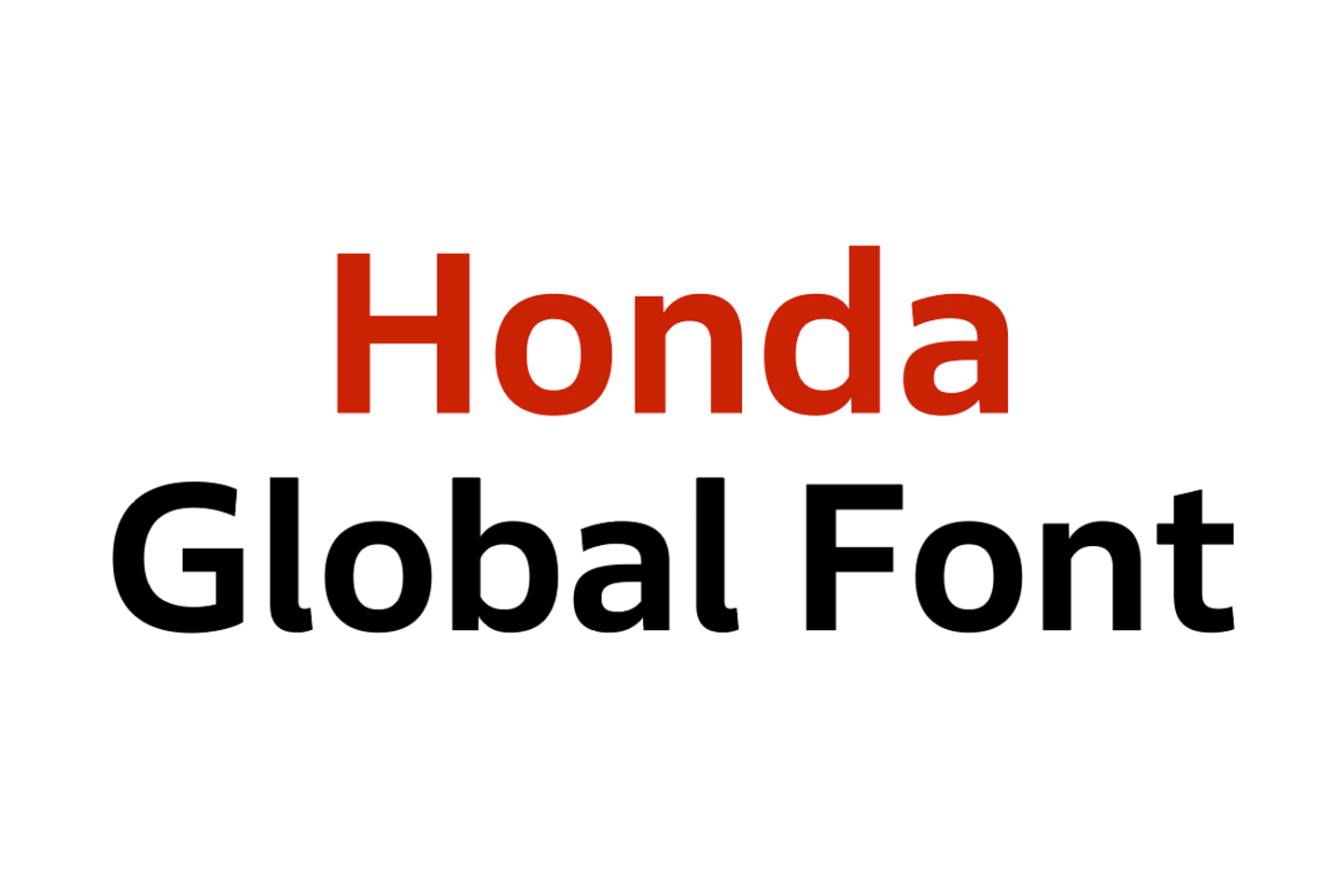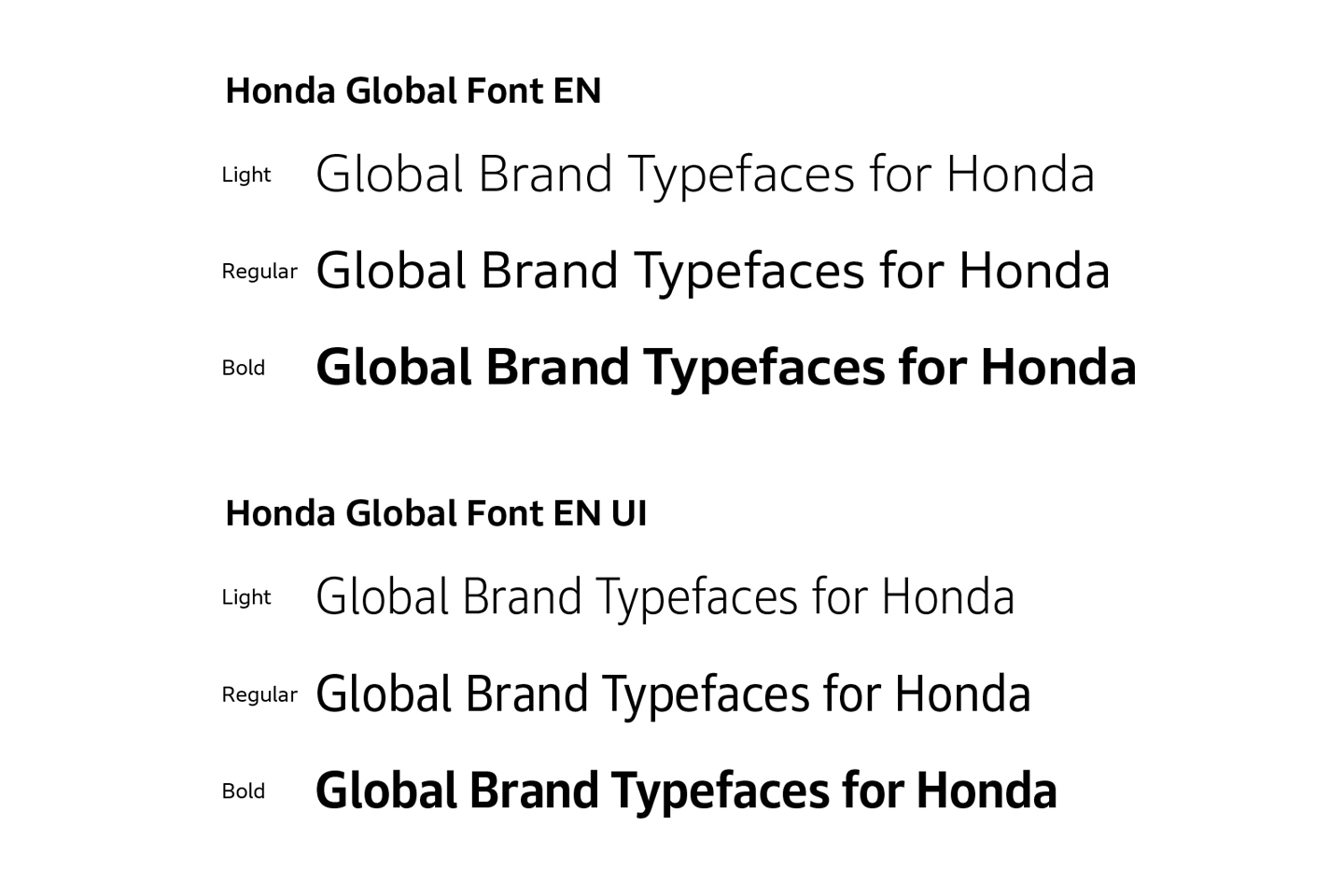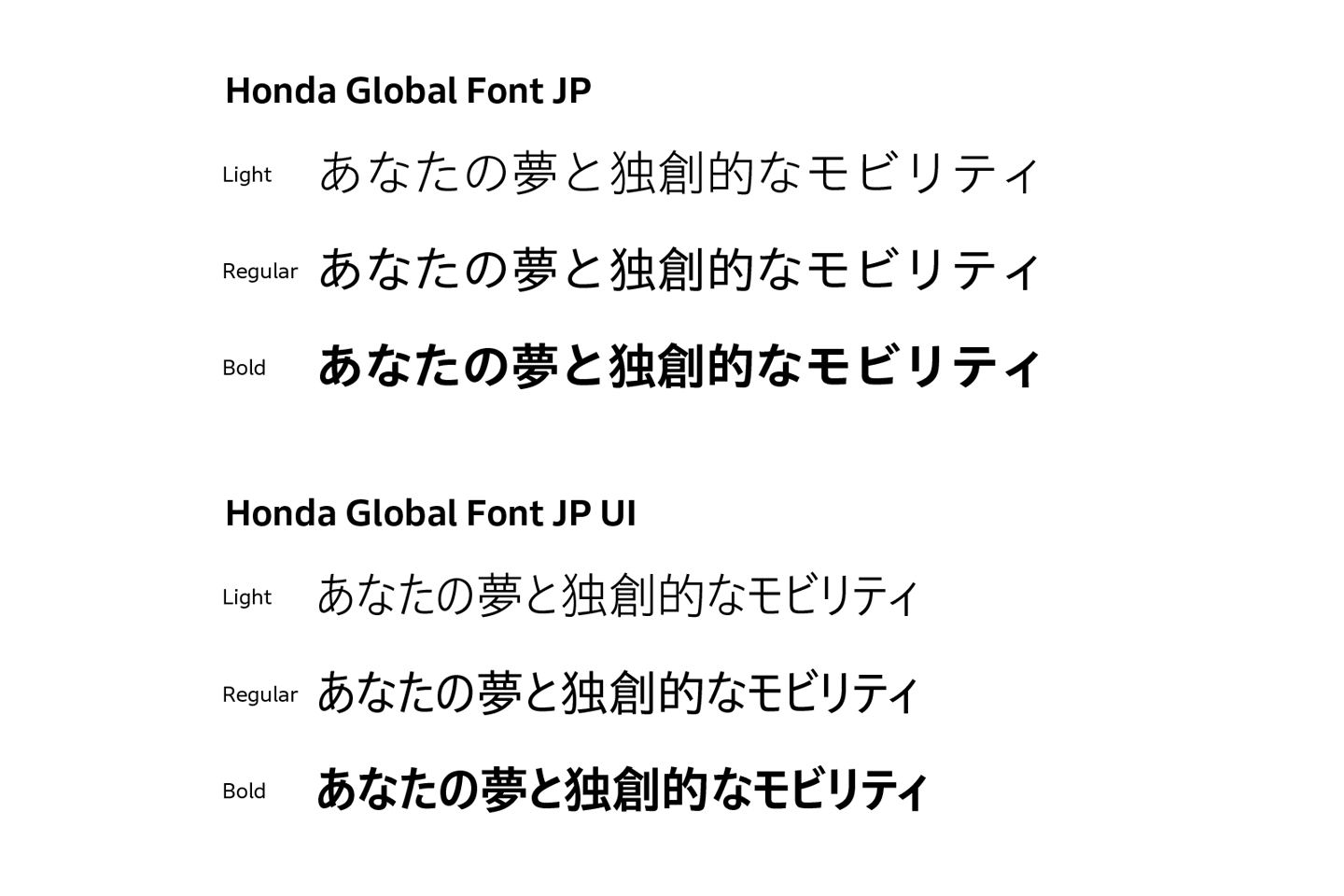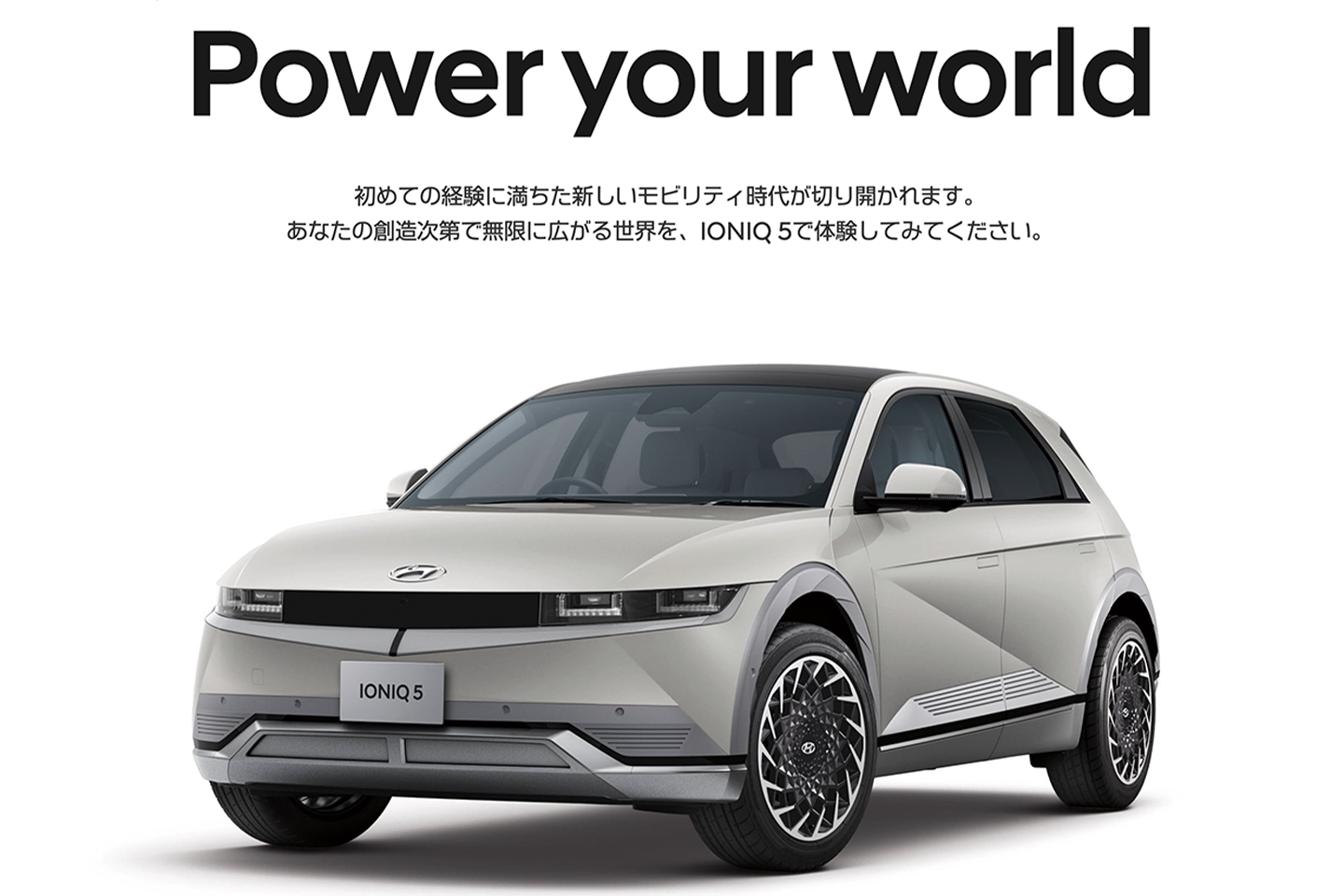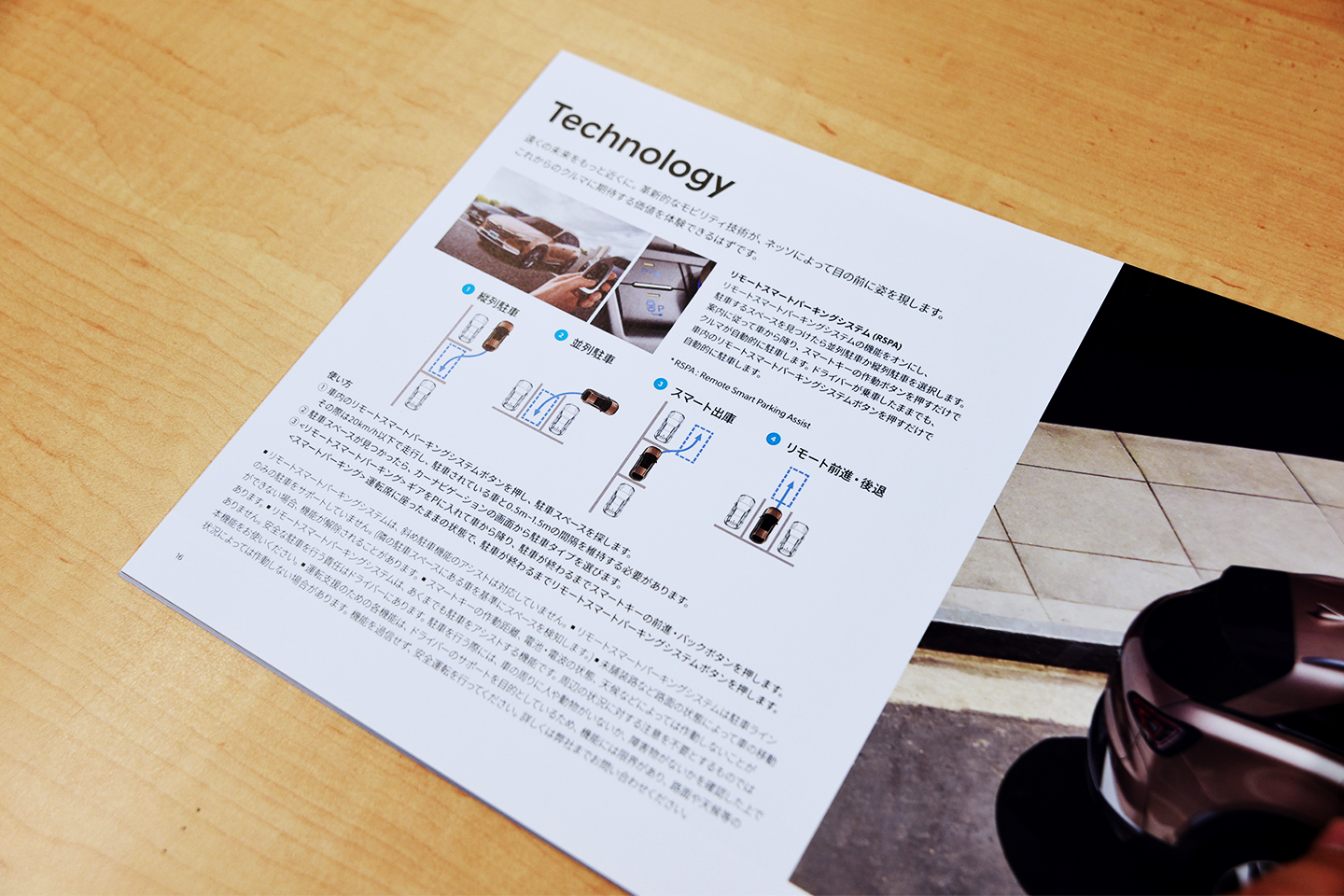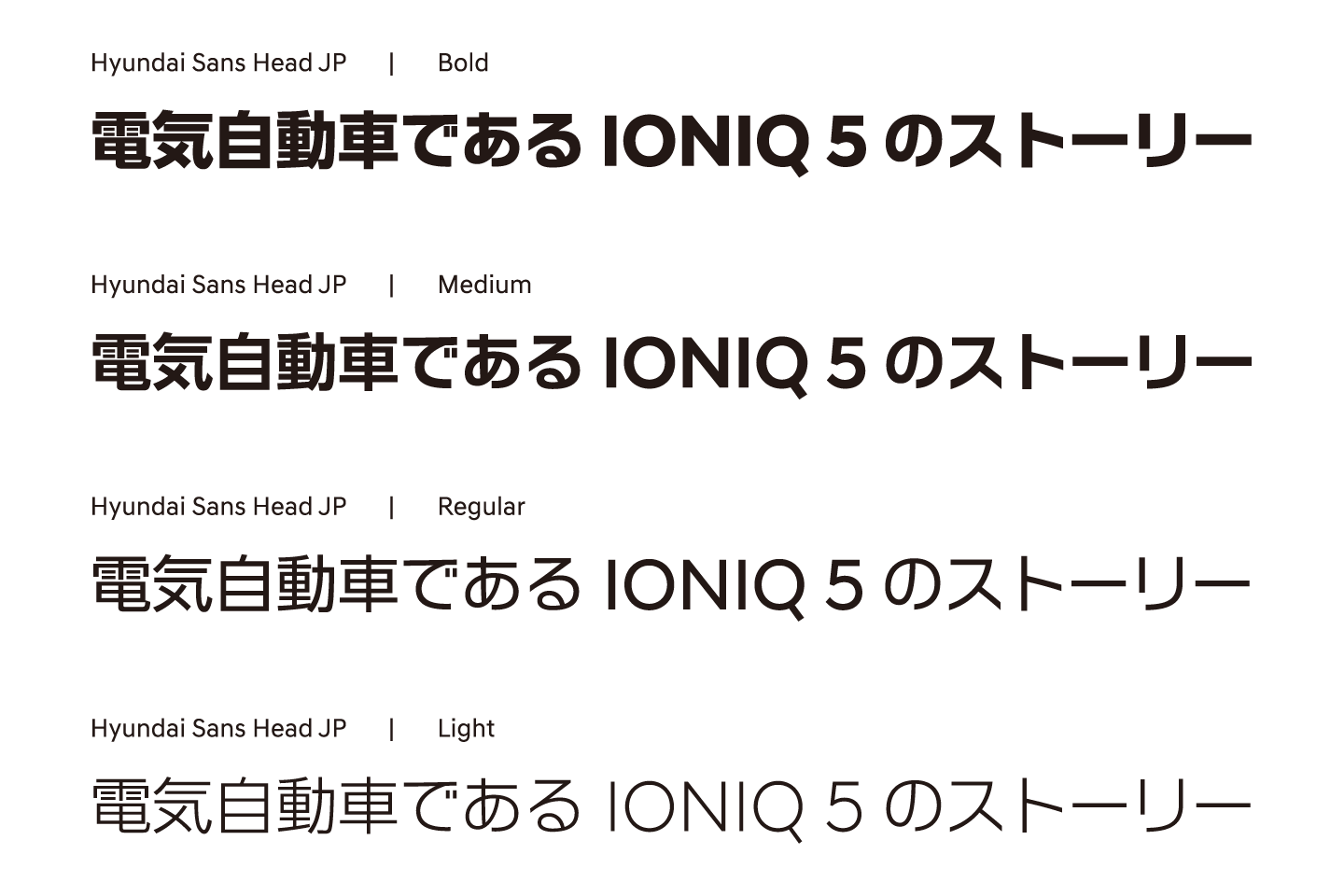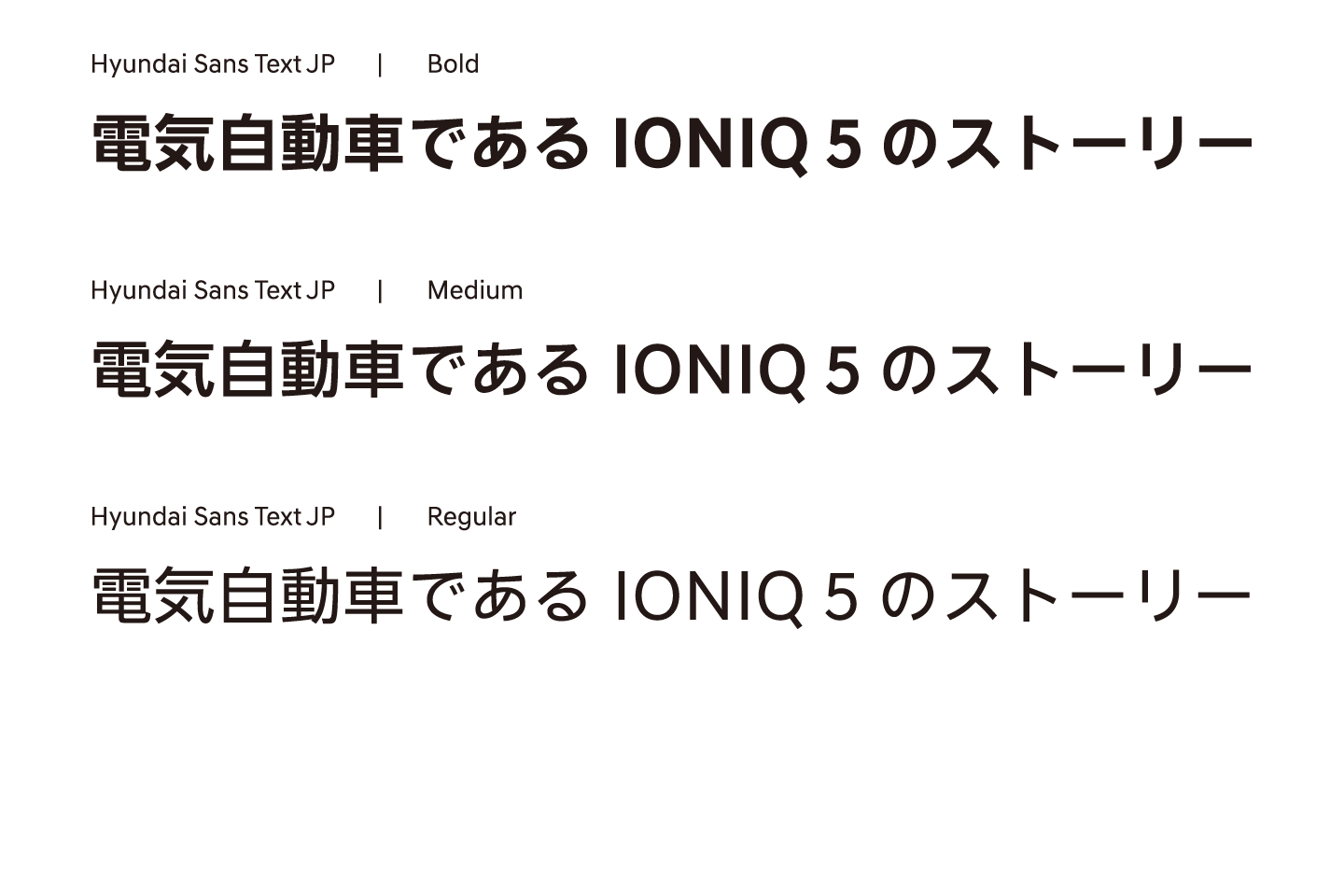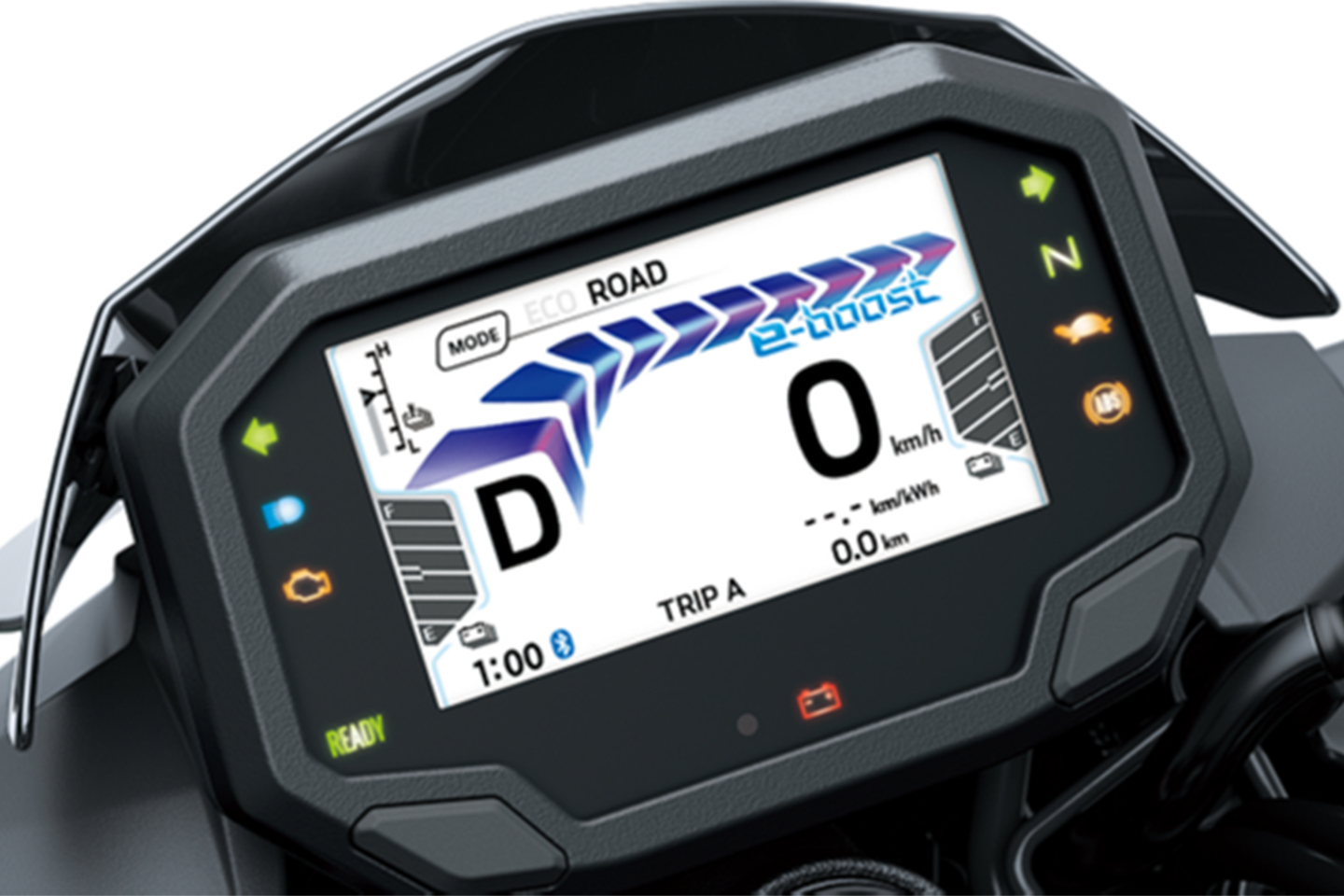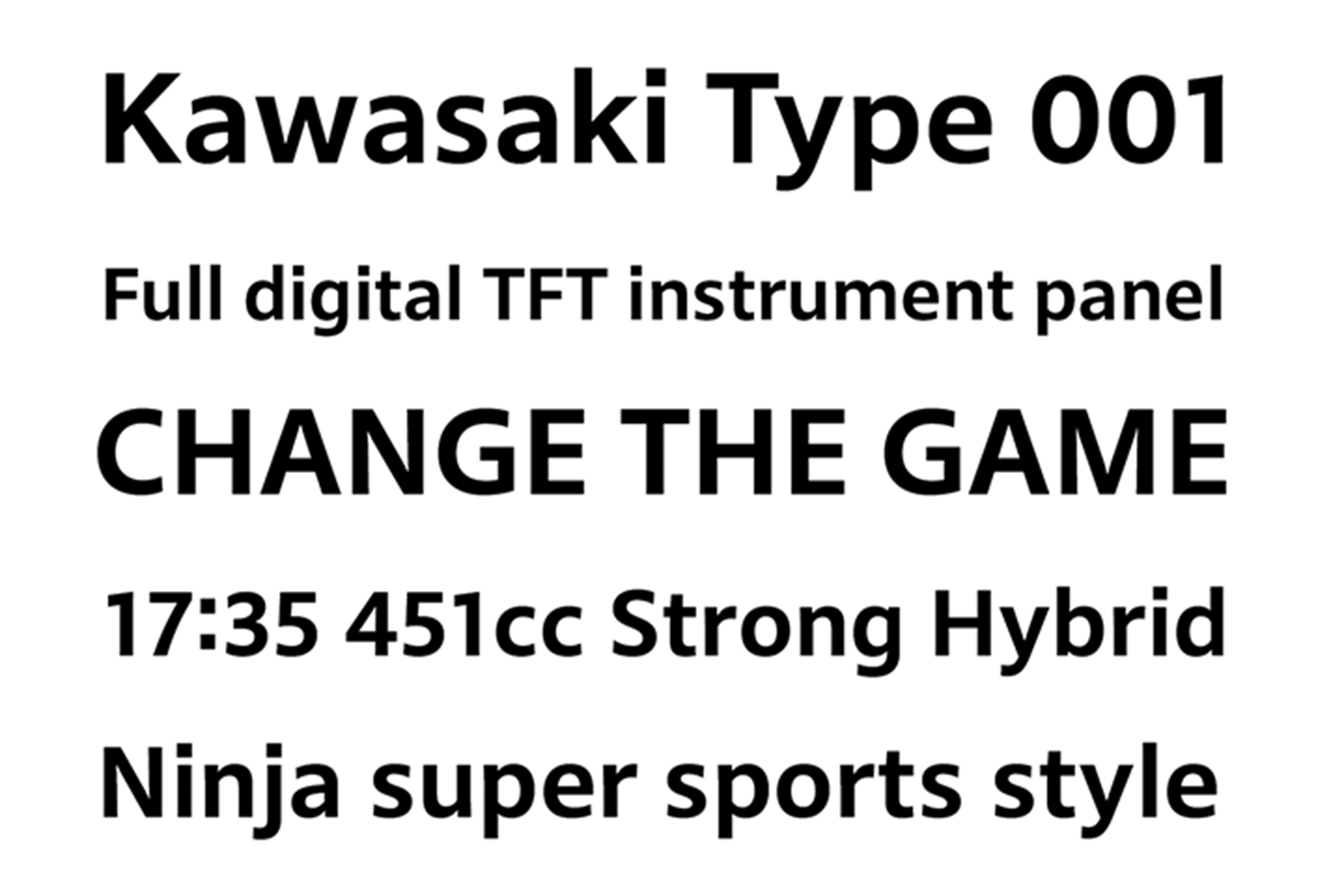
- フォント名:甲子園フォント
- プロジェクト期間:2年
開場100周年を迎えた記念事業として、阪神甲子園球場が長年大切にしてきた「甲子園文字」の伝統継承をコンセプトに開発。主に阪神甲子園球場のスコアボードや球場オリジナルグッズに使用。
コーポレート、商品、製品、サービス、店舗。
ブランディングや販促のみならず、
文字コミュニケーションのすべてが昇華する、
世界にたったひとつのオリジナルフォント。
開場100周年を迎えた記念事業として、阪神甲子園球場が長年大切にしてきた「甲子園文字」の伝統継承をコンセプトに開発。主に阪神甲子園球場のスコアボードや球場オリジナルグッズに使用。
「Hondaらしさ」を発信するため、グローバル市場での使用を前提に、コミュニケーション領域から各事業のプロダクトまで幅広く活用できる欧文と和文のコーポレートフォントを開発。
日本の食卓を彩り、多くの人々に愛されてきた「味ぽん®」の発売開始60周年を記念し、95文字のひらがなと名前入りラベルなどの展開を想定して「ぽん」「味ぽん」のロゴのフォントを開発。
国内有数のビジネスチャットを展開する同社が10周年を機に実施したリブランディングでは、ブランドコンセプトを体現し、ロゴのデザインとの親和性を図り、和文と欧文混在の社名も打ち出しやすく。
100%果実発酵酢で人気のビネガードリンク「美酢(ミチョ)」の日本販売開始10年を機に、象徴的な雫マークやロゴ、パッケージなどで使用頻度が高い135文字を開発、デザインの自由度が向上。
日本での乗用車マーケットへの再参入を機に、同社が持つグローバル向け欧文コーポレートフォントから和文フォントをオリジナル開発、デジタル中心の販売も意識した人間らしさや温かみを実現。
同社初の電動およびハイブリッドモーターサイクルの市場投入を機に、社のアイデンティティを体現するシグネチャーフォントを開発、振動、天候、昼夜に関わらず高い視認性を実現。
※画像はNinja e-1/Z e-1用メーター
ブランディングで悩ましい課題となるのが書体=フォントの選定。
モリサワのオリジナルフォントなら、全社規模からブランド単体規模まで、現場のあらゆる要件の開発にもフレキシブルに応えます。
統一したブランドイメージを表現するため、コーポレートフォントを採用する企業が増えつつあります。
ロゴをベースにしたコーポレートフォントの開発や、
お客様が所有する欧文フォントに合わせた和文コーポレートフォント開発などにもお応えします。
漢字や文字数が多く独自フォントの開発が困難とされがちな日本語、かなをアレンジするだけでもイメージを作ることができます。例えば、企業のロゴなどをモチーフにかなのデザインを変更し、表現したいブランドイメージを実現します。
同じ漢字に異なるかなを合わせるだけで、表情が変わります。かなや漢字の一部などに独自のデザインを取り入れることもできます。
例えば、グローバル向けにお客様が所有する欧文コーポレートフォントに合わせた和文コーポレートフォントの開発や、欧文と和文をマージしたフォントをご提供することも可能で、便利にお使いいただくことができます。
和文と欧文をバラバラで使用する場合、ベースラインやサイズの調整が必要です。モリサワでは、最適に調整、マージし、ご提供が可能です。
商品や製品プロダクトは、ロゴ、パッケージ、Webサイト、店頭POPなど販促物の制作が不可欠。
使用目的に合った仕様やデザインで、
統一した世界観を表現するプロダクトや販促物をよりスムーズに制作するお手伝いをします。
アプリやデジタル機器のモニターなど、使用目的に合わせ、最適なフォントをご提案します。組込みフォントやWebフォントなど、ニーズに合わせたサイズや仕様にてご相談が可能です。必要な文字のみなどのご要望にもお応えします。
消費財などのナショナルブランドや商品シリーズのパッケージや販促物などの制作において、統一した世界観を効率的に演出するためのオリジナルフォントをご提案します。
企業名や固有名詞に使われる旧字体や異体字、
ビジネス上使用頻度の高い特殊な記号やマーク、文字などは、実は頻発するニーズ。
特定の文字だけを異なる字形にカスタマイズするなど、部分的な開発にもお応えします。
創業者の氏名や、化学や数学の記号や単位など、ビジネス上の資料やWebサイトに不可欠のため、画像にして掲載されていることもあるかもしれません。フォント化すれば、サイズ変更も容易になり、SEOにも対応、1文字の部分開発からお応えします。
モリサワのフォントライブラリーの中からご要望に近いフォントサンプルをご提案し、詳細なご要望のイメージをすり合わせます。
デザインの制作過程ではフィードバックをいただき、調整を行うなどしながら、理想のフォントデザインに仕上げていきます。